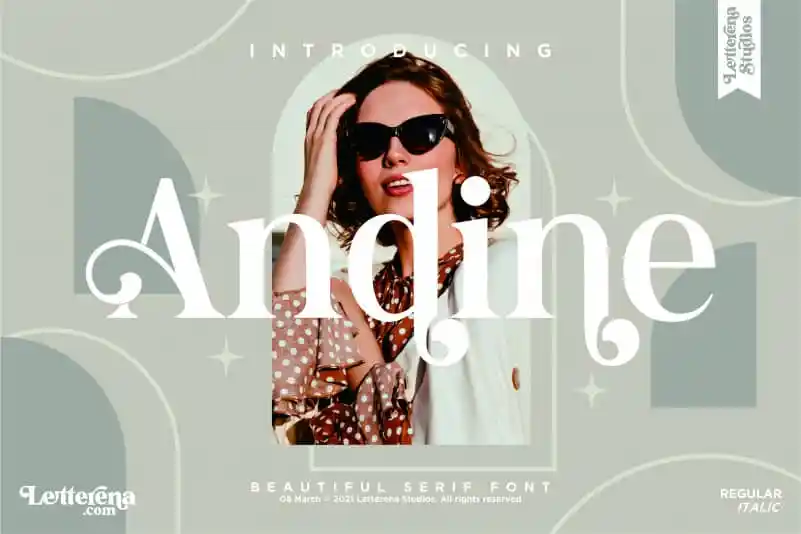
A fonte serif Andine Font é uma escolha excepcional para projetos onde a elegância se une à sofisticação. Sujeitável a diversos tipos de trabalho, como logotipos, marcas e embalagens, também atende aos mais variados ambientes, desde mugs até cartões de convite, capas de livros e sacolas de shopping. Inspirada em um estilo elegante que traz uma atmosfera aconchegante e sofisticada, Andine é perfeita para projetos que exigem um toque refinado e luxuoso. Seja você criador de marca, designer de embalagens ou qualquer profissional que busque um acabamento impecável em seus trabalhos, Andine será a escolha certa. Com sua tipografia serif cuidadosamente elaborada por Designer da Letterenastudios, esta font oferece uma experiência visual única. Suas linhas elegantes e detalhes sofisticados permitem transpor o seu design de maneira elegante e impecável em qualquer mídia. A letra de Andine é perfeitamente adaptada às necessidades do seu projeto, sejam eles grandes ou pequenos, complexos ou simples. Andine atinge um alto nível de qualidade com sua tipografia cuidadosamente desenvolvida, tornando-se uma ótima opção para qualquer projeto que deseje destacar a sua beleza e elegância. Não importa o tamanho do seu trabalho ou o impacto que você quer transmitir — Andine é capaz de capturar essa essência com um toque sofisticado e refinado.